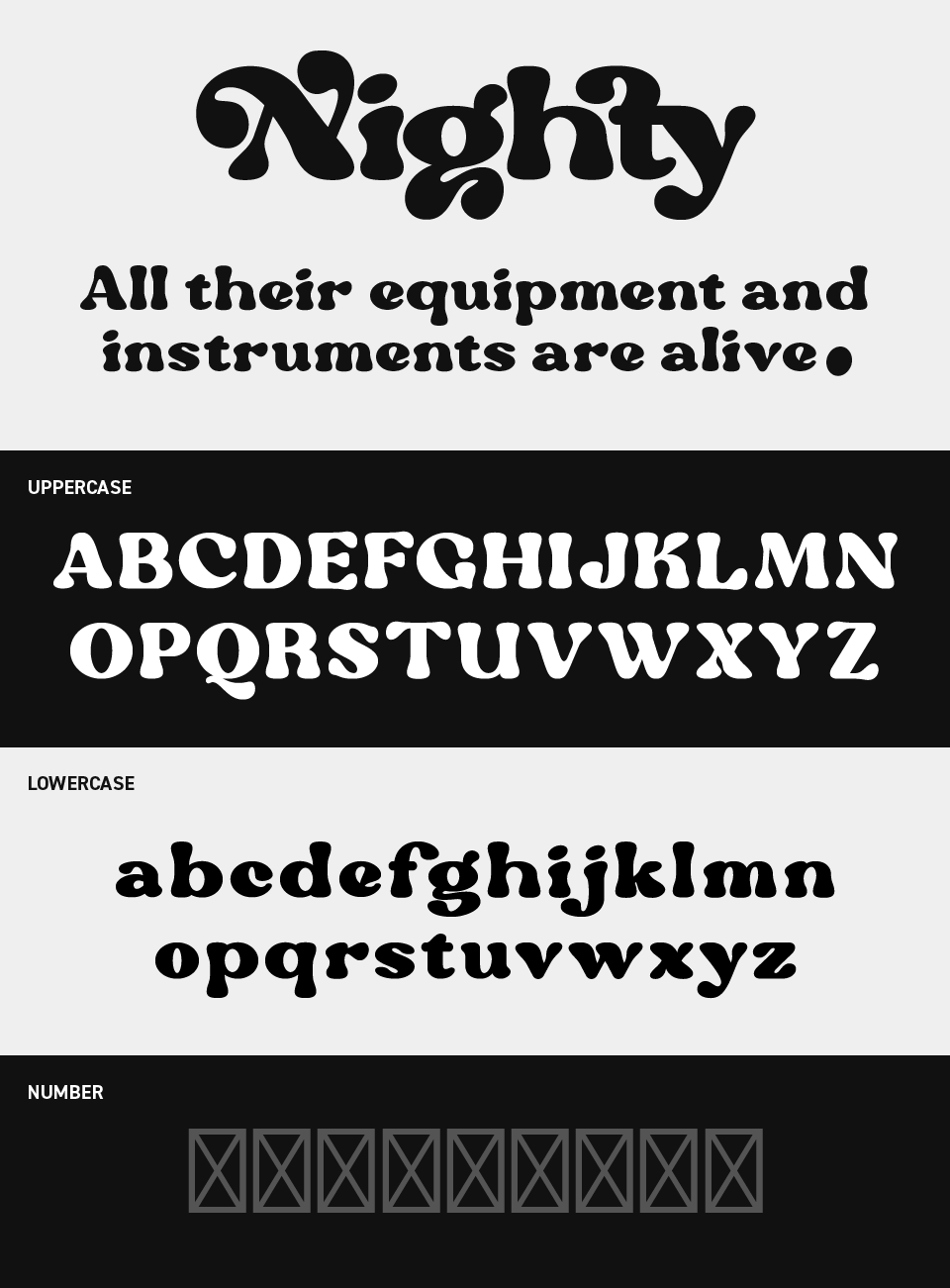
Nightyフォントは、むっちりと丸みを帯びたシルエットに、ちょっとしたねじれやうねりが加わった、ユニークな雰囲気をもつディスプレイフォントです。
まるで夜の空気がとろけるような、やさしく幻想的な印象があります。
文字の組み付かれリズミカルに揺れる字形は、どこかヴィンテージ感もあり、60〜70年代のレトロポップなテイストにもぴったり。かわいさとおしゃれさが同居した、印象に残るフォントです。
収録文字は、大文字/小文字の収録となっています。